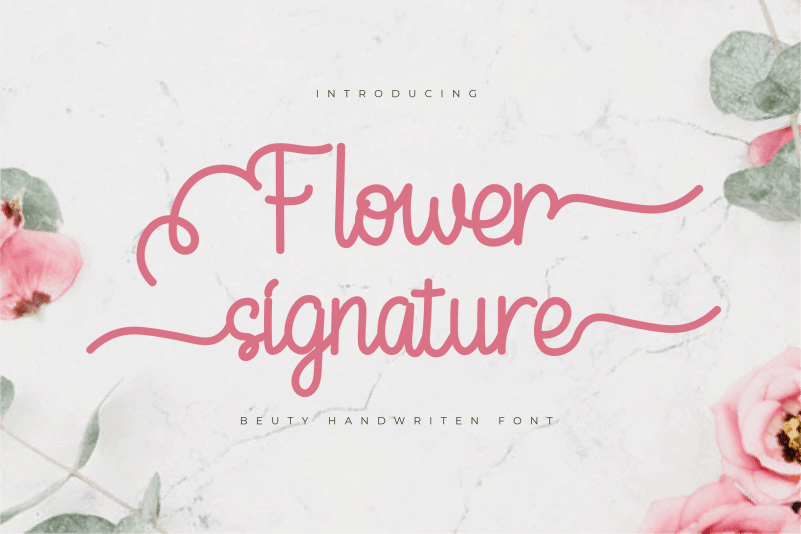
Flower Signature Script Font – Download Grátis
A Flower Signature Script Font é uma elegante tipografia feita à mão, ideal para elevarem seus projetos de design ao nível mais alto — seja para branding, cabeçalhos, designs de casamento, convites, assinaturas, logotipos, rótulos e muito mais. Seu charme e delicadeza dão um toque único e sofisticado a qualquer projeto. Este font é perfeito tanto para designers profissionais quanto para aquelas que buscam adicionar um detalhe especial à sua produção gráfica. Com a Flower Signature Script Font, seu trabalho não ficará apenas no papel — ele se tornará uma verdadeira obra de arte.